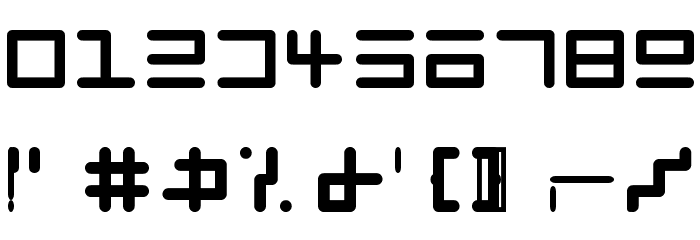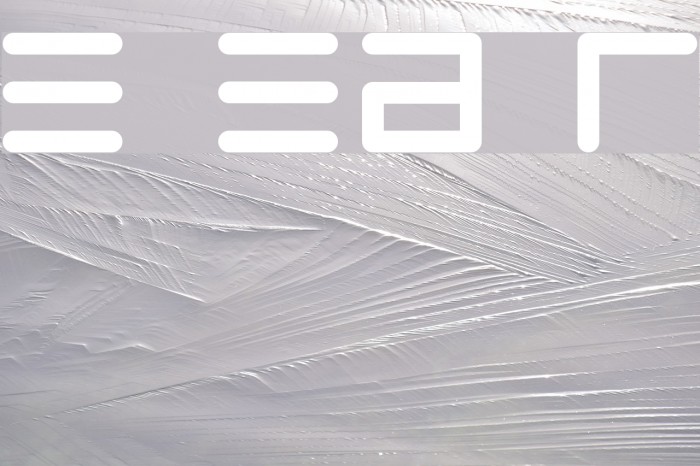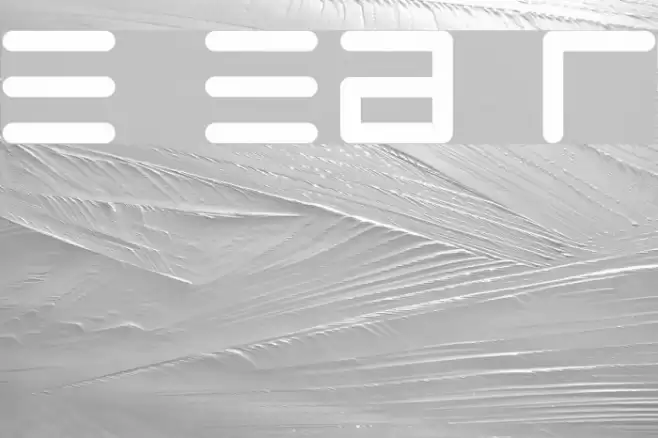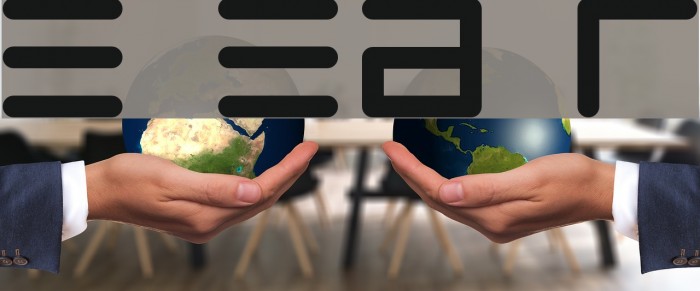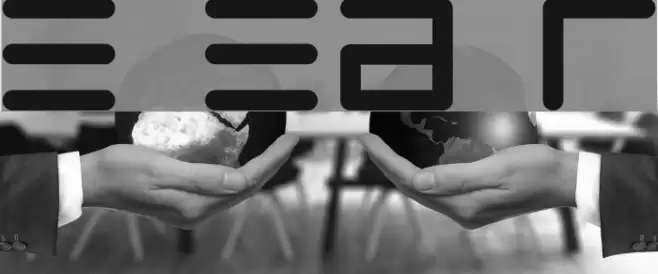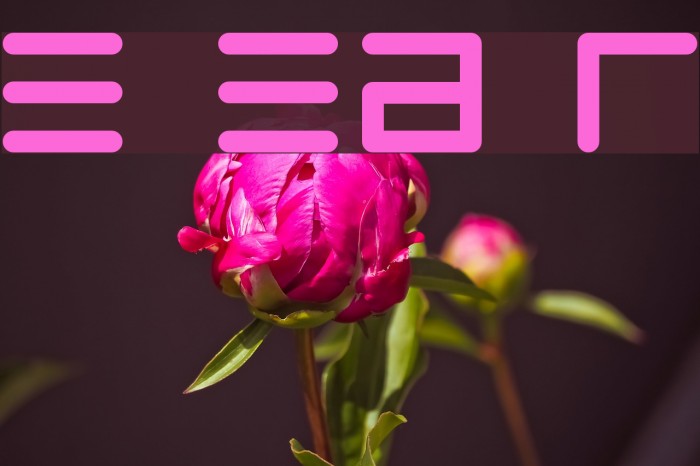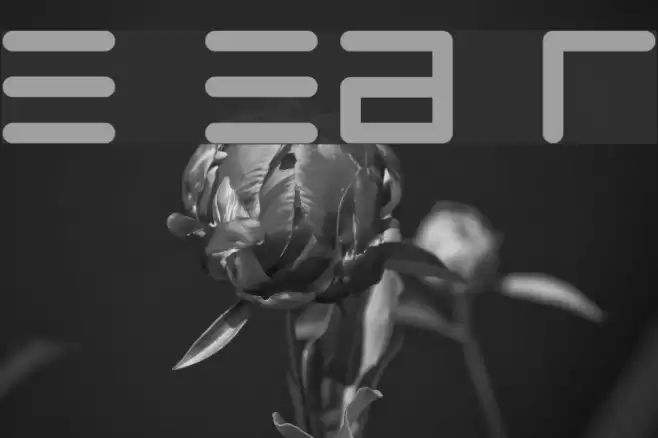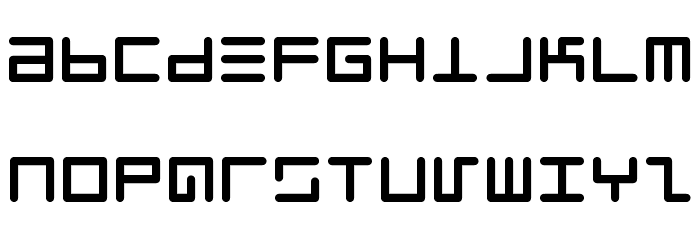
Eppy Evans Round Font
| Caz de utilizare | Logos, Headlines, Digital interfaces |
| Proiecte propuse | Ideal for tech branding, digital interfaces, futuristic posters, and modern graphic design projects. |